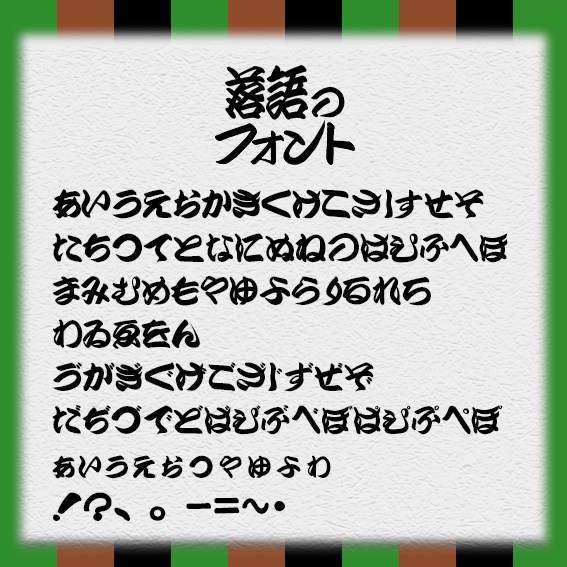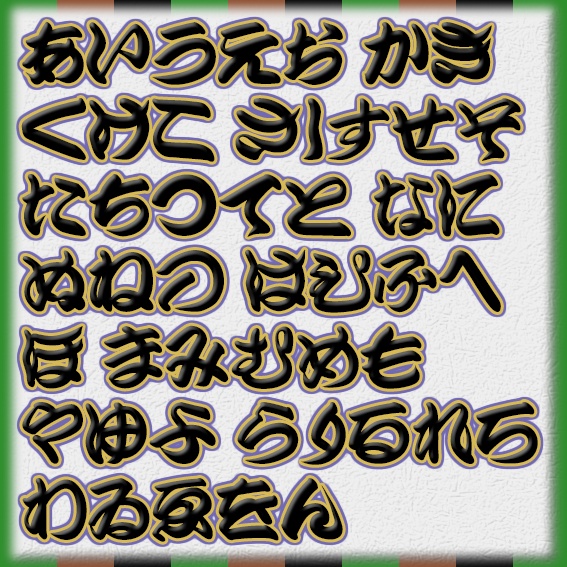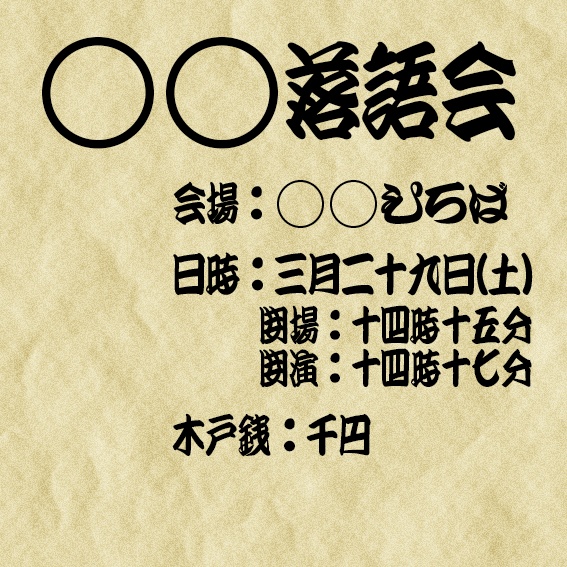
落語のフォント
落語用の寄席文字の個人製作フォントです。 手書きであるため、多少のクセがあります。 現在は平仮名と一部記号のみですが、順次拡大予定です。 (カタカナが先かよく使う漢字が先か、、、) 縦書きにも対応しています。
ーーー収録文字についてーーー
1.ひらがな 2.記号(一部) !?、。・ー~=は対応しています。(すべて全角) 3.その他(多用漢字) 月火水木金土日、年、時分、木戸銭、落語、会、開、演、場、千、百、円、圓、:、()、漢数字(一~十)、アラビア数字(全角)を追加しました! ※カタカナ、常用漢字、記号など順次追加予定! ※ご要望ありましたら優先して追加しますので『hottokohi1996@gmail.com』までご連絡ください!